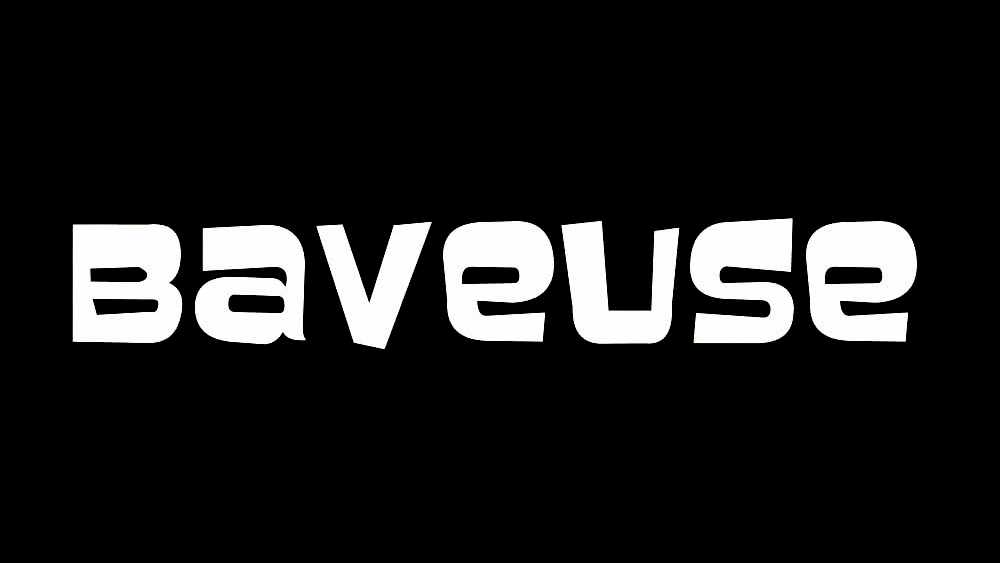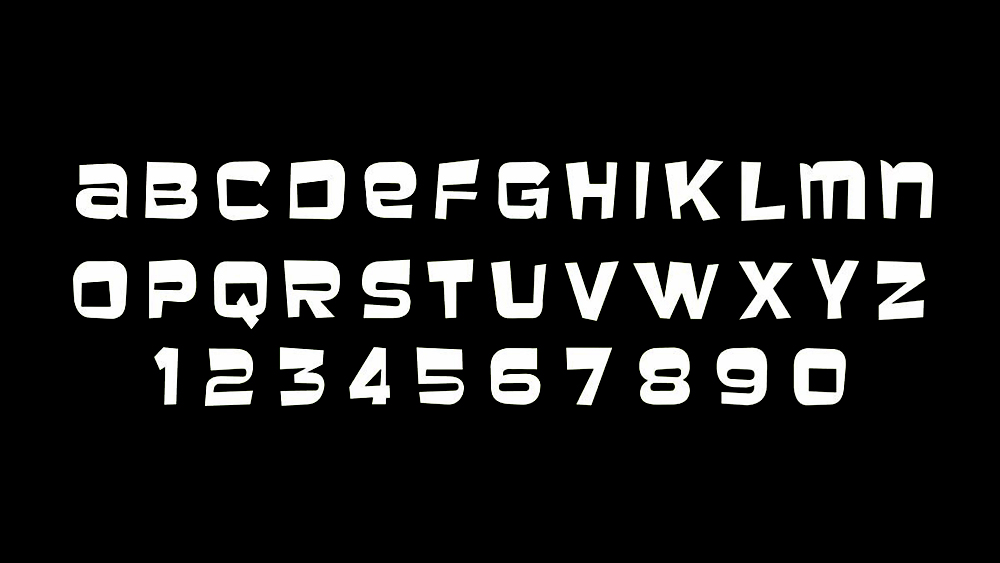
فونت پرمیوم و انگلیسی Baveuse Font یک فونت در دو سبک تو پر و تو خالی که برای انواع پروژه برندسازی مانند نام تجاری، لوگو، تیتر و…
فونت پرمیوم و انگلیسی Baveuse Font یک فونت در دو سبک تو پر و تو خالی که برای انواع پروژه برندسازی مانند نام تجاری، لوگو، تیتر و سرفصل و… مناسب است.
مزایای استفاده از فونت لاتین Baveuse چیست؟